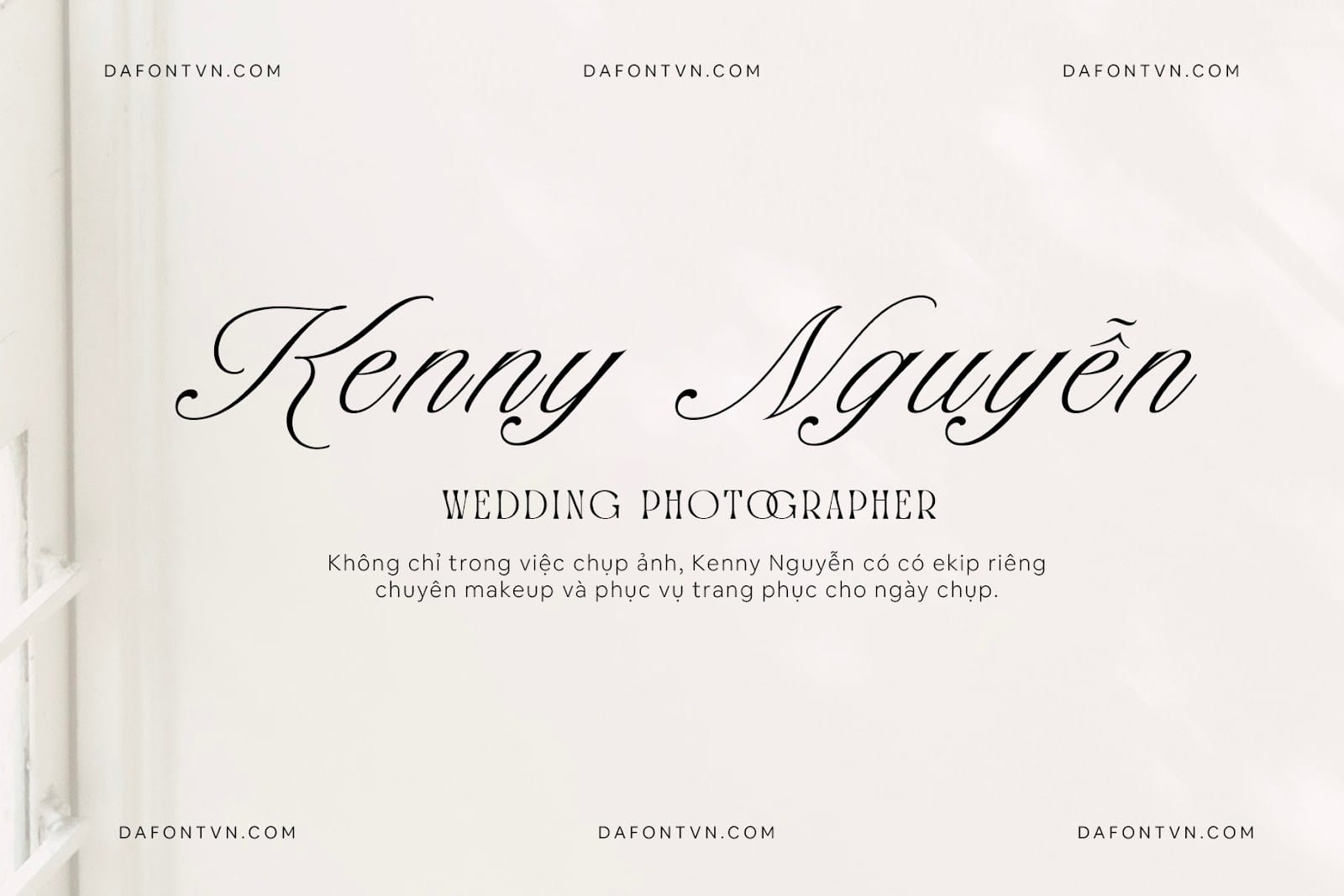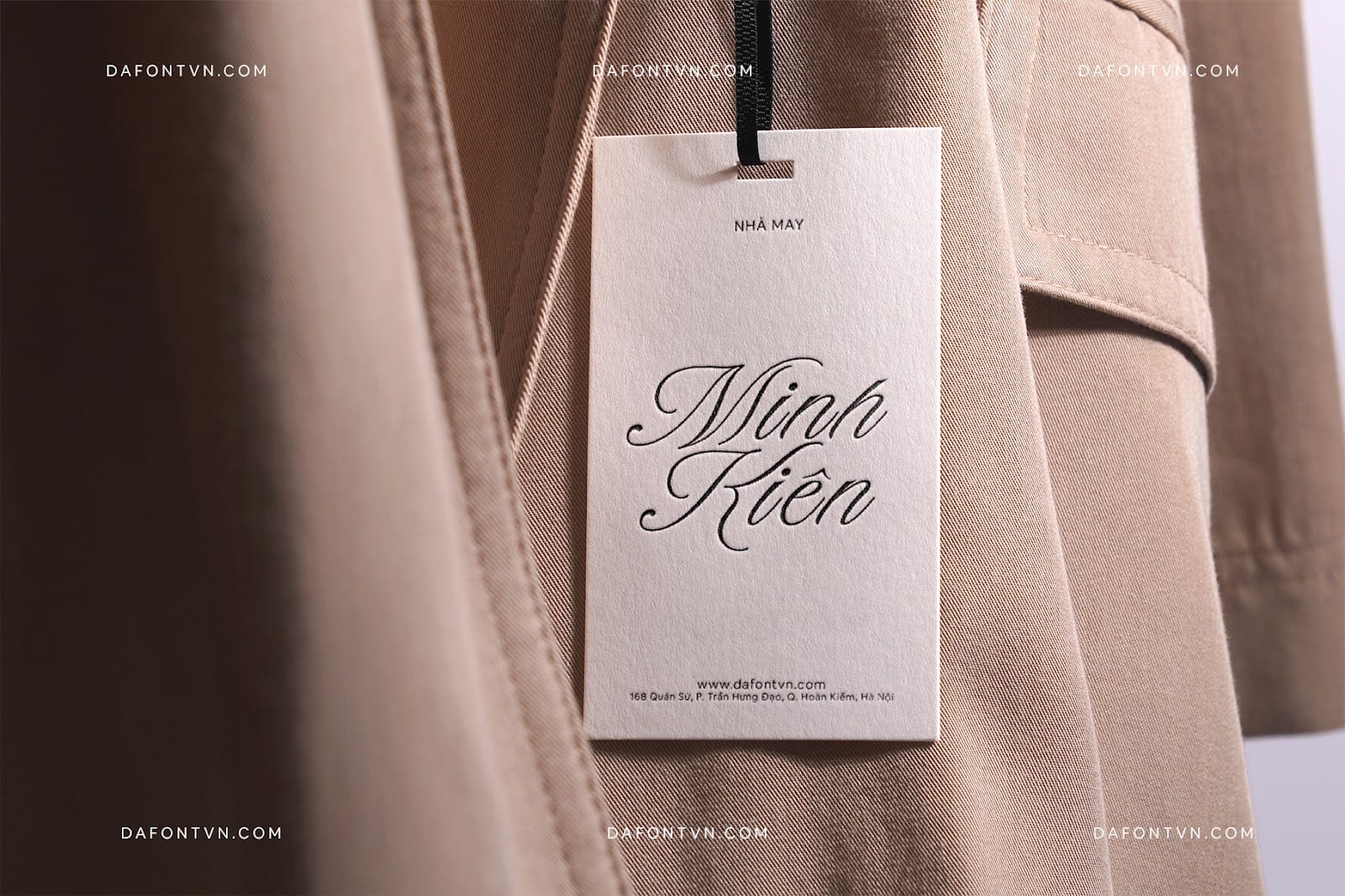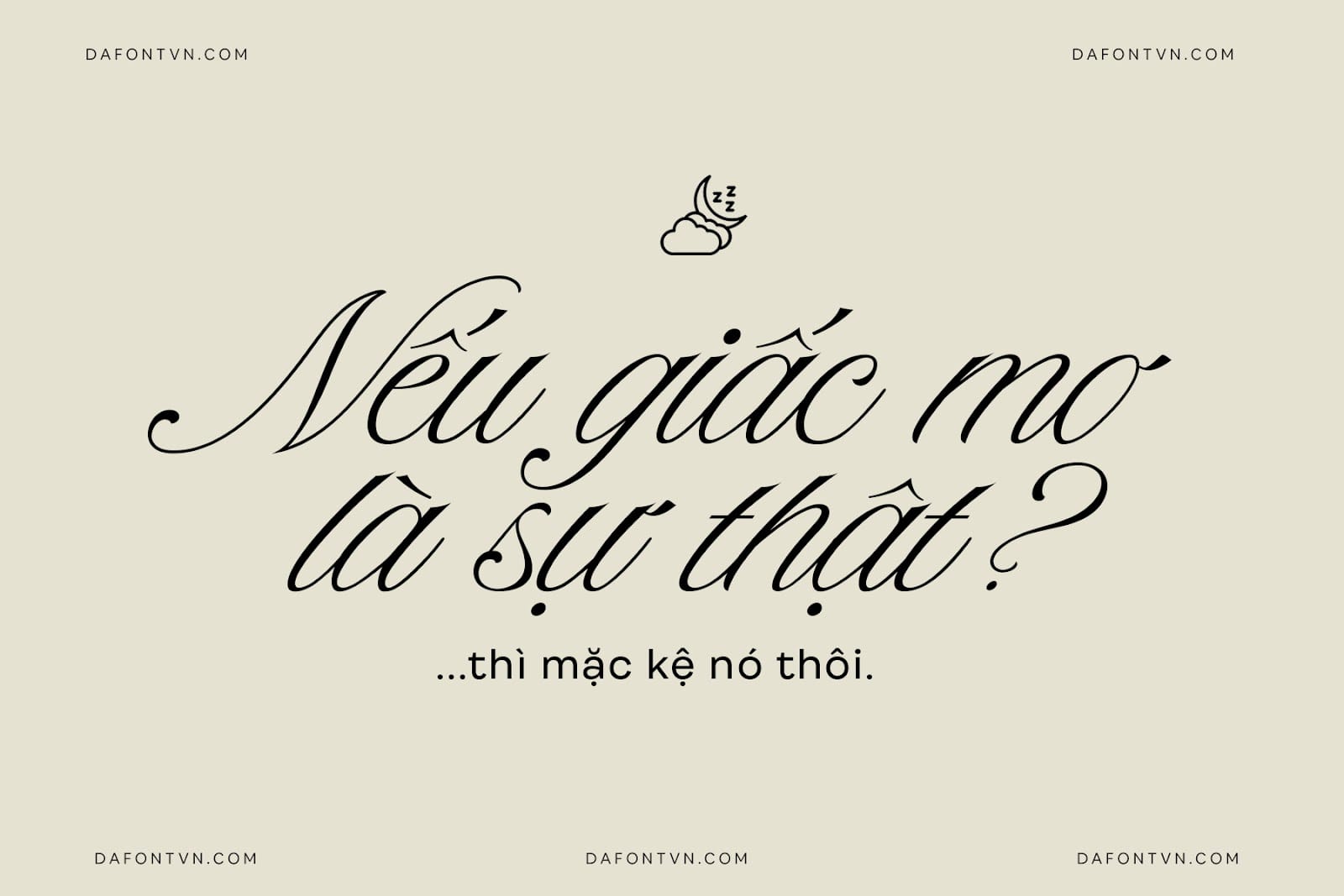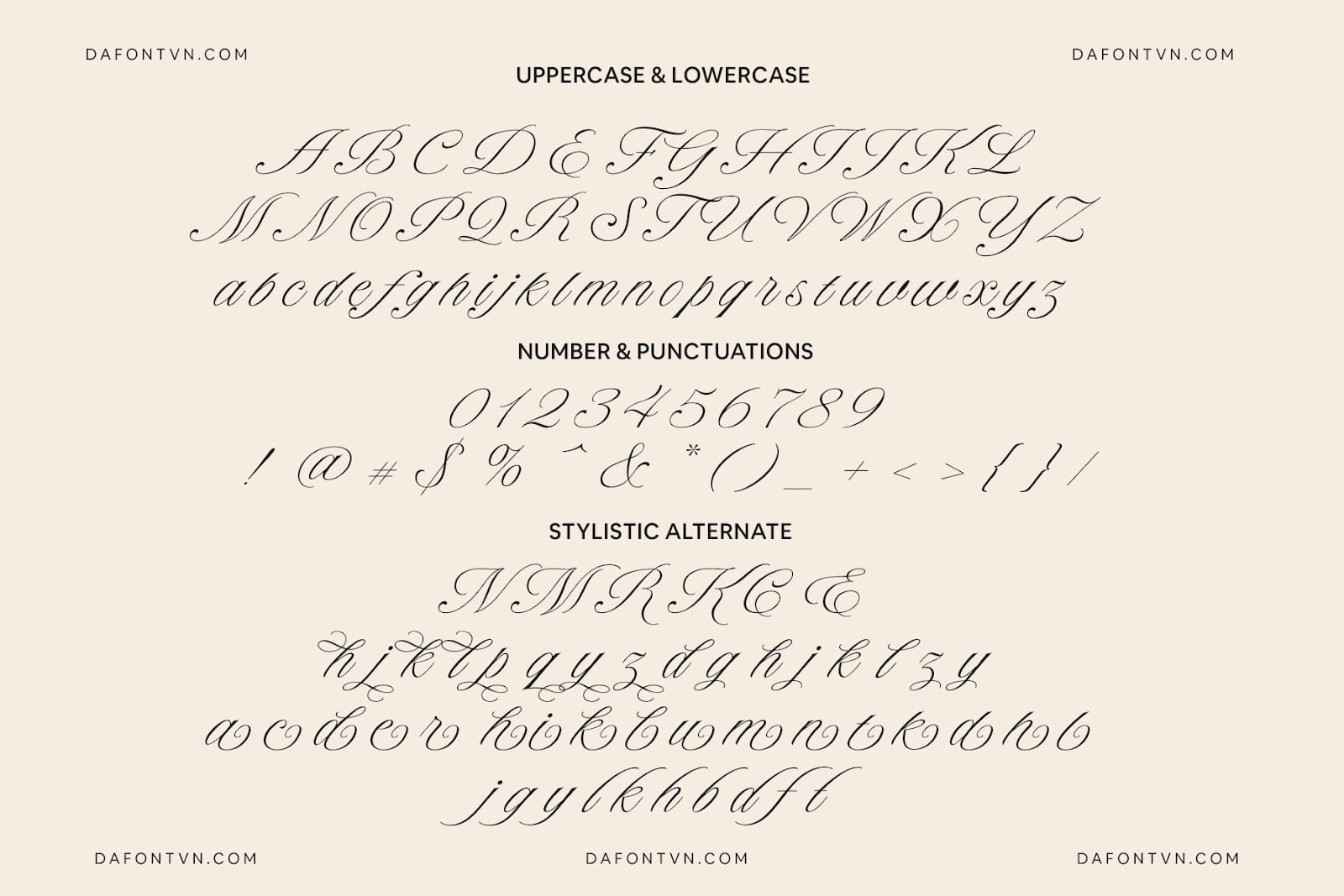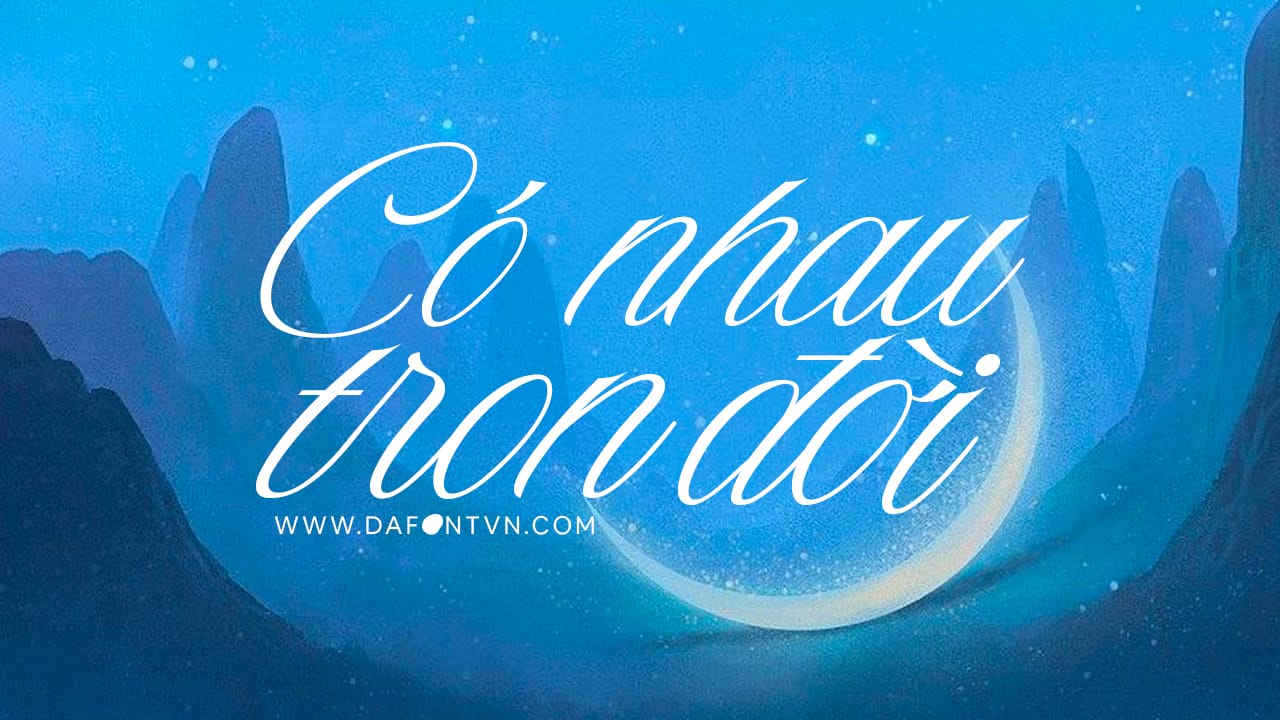
Rosmerta Font – Là kiểu font viết tay thanh lịch, sang trọng, tinh tế và có một chút gì đó cổ điển. Kiểu chữ Rosmerta có một vài lựa chọn thay thế về và chữ ghép để bạn có thể kết hợp tạo ra những thiết kế tốt nhất của mình.
Font Rosmerta việt hóa hoàn toàn phù hợp cho thiết kế bố cục cho các trích dẫn hoặc nội dung, được sử dụng tốt nhất làm kiểu chữ hiển thị cho tiêu đề, logo, nhãn hiệu, tạp chí, bao bì sản phẩm, thiệp mời đám cưới,…
Rosmerta mang lại cảm giác hoài cổ và duyên dáng cho bất kỳ dự án nào. Tận hưởng nét quyến rũ cổ điển với phông chữ tinh tế và linh hoạt này.